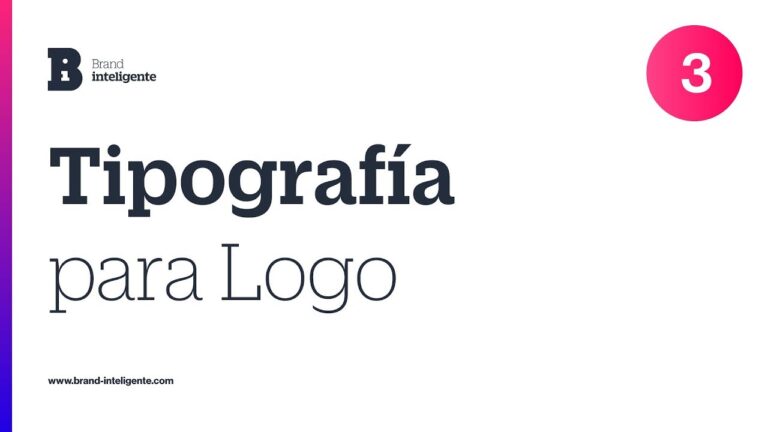
Guía de selección de tipografías para logotipos
En el mundo del diseño de logotipos, la selección de tipografías juega un papel crucial en la creación de una imagen de marca impactante y memorable. La elección de fuentes puede transmitir la personalidad de la empresa, su estilo y sus valores. En este artículo, exploraremos cómo elegir las tipografías adecuadas para logotipos que destaquen y se conecten con la audiencia de manera efectiva. ¡Descubre cómo darle vida a tu marca a través de la tipografía!
Tampoco es aconsejable emplear tipos de letra muy frecuentes en textos y documentos, como Arial. En general, las que mejor funcionan son las clásicas y más sencillas, como Helvética, Roboto, Soho, Din o Futura. Es importante elegir una fuente que sea legible y que represente la identidad de la marca de manera efectiva, evitando las modas pasajeras que puedan hacer que el logo parezca desactualizado en poco tiempo.
¿De qué manera se puede determinar el tipo de letra de un logotipo?
Un buen recurso para identificar la tipografía de un logotipo es WhatTheFont para móvil. Con esta aplicación, simplemente toma una foto del texto impreso en el logo y la App buscará las fuentes que coincidan con la muestra. Es sencillo y rápido, ideal para aquellos que no saben cómo descubrir el tipo de letra utilizado.
Al utilizar WhatTheFont, solo necesitas ajustar la foto que tomaste del logo y separar los caracteres para que la aplicación pueda analizarlos correctamente. Una vez completado este paso, las fuentes que se asemejen a la muestra aparecerán en la parte inferior de la pantalla, facilitando así la identificación del tipo de letra utilizado en el diseño.
Con esta herramienta, saber el tipo de letra de un logotipo se vuelve una tarea fácil y accesible para cualquier persona. WhatTheFont para móvil ofrece una solución rápida y eficaz para aquellos que desean conocer más sobre la tipografía utilizada en diferentes diseños de logos.
¿Qué es la tipografía de un logotipo?
La tipografía de un logotipo es un componente esencial en la identidad de una marca, ya que ayuda a comunicar de manera efectiva el mensaje de la empresa a través de la escritura. Es importante elegir una tipografía que refleje la personalidad y los valores de la marca para transmitir una imagen coherente y profesional.
La tipografía no solo se trata de elegir un estilo de letra atractivo, sino también de asegurarse de que sea legible en diferentes tamaños y formatos. Una tipografía bien diseñada puede mejorar la percepción de la marca y crear una conexión emocional con el público objetivo. Es fundamental encontrar el equilibrio adecuado entre la creatividad y la funcionalidad para lograr un logotipo exitoso.
Al seleccionar la tipografía para un logotipo, es crucial considerar la consistencia con la identidad visual de la marca, así como la versatilidad de la tipografía en diferentes plataformas y medios. La tipografía adecuada puede hacer que un logotipo destaque y sea fácilmente reconocible, lo que contribuye a fortalecer la presencia de la marca en el mercado.
Tipografías que destacan: ¡Haz que tu logo brille!
Dale a tu marca el reconocimiento que se merece con una tipografía que destaque por encima de las demás. Un logo bien diseñado con una fuente llamativa puede captar la atención de tu audiencia de manera instantánea. La elección de la tipografía adecuada puede hacer que tu logo brille y se destaque entre la multitud, transmitiendo la personalidad y el mensaje de tu marca de forma clara y efectiva.
No subestimes el poder de una tipografía bien elegida para representar tu marca. Desde fuentes elegantes y sofisticadas hasta modernas y audaces, hay una amplia gama de opciones para que tu logo se destaque y deje una impresión duradera en tus clientes. ¡Haz que tu logo brille con una tipografía que refleje la identidad de tu marca y la haga destacar en un mar de competencia!
El arte de elegir la tipografía perfecta para tu marca
En el mundo del diseño gráfico, la tipografía juega un papel fundamental en la identidad de una marca. Elegir la tipografía adecuada puede transmitir la personalidad y valores de tu empresa de una manera efectiva. Es importante seleccionar una fuente que sea legible, versátil y que se adapte al estilo de tu marca.
La tipografía no solo se limita a la elección de una fuente específica, sino que también incluye consideraciones como el tamaño, espaciado y color del texto. Estos elementos deben trabajar en conjunto para crear una experiencia cohesiva y memorable para tus clientes. Al combinar diferentes tipos de letras de manera equilibrada, puedes destacar información importante y guiar la atención del espectador de manera efectiva.
Al final del día, la tipografía es una herramienta poderosa que puede marcar la diferencia en cómo tu marca es percibida por el público. Dedica tiempo a explorar y experimentar con diferentes fuentes para encontrar la que mejor se adapte a la personalidad de tu empresa. Recuerda que una tipografía bien elegida puede ayudarte a destacar entre la multitud y a crear una identidad visual sólida y coherente para tu marca.